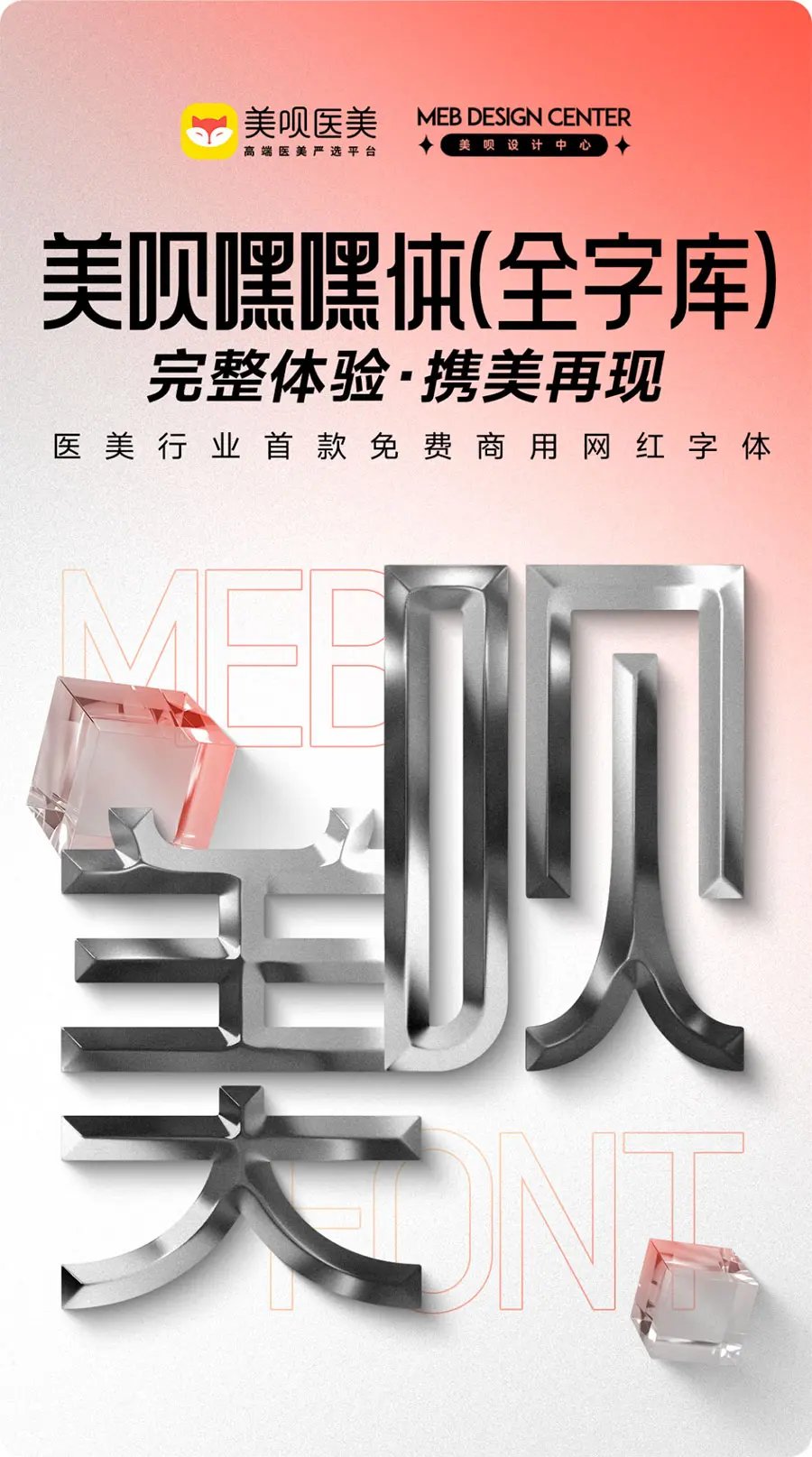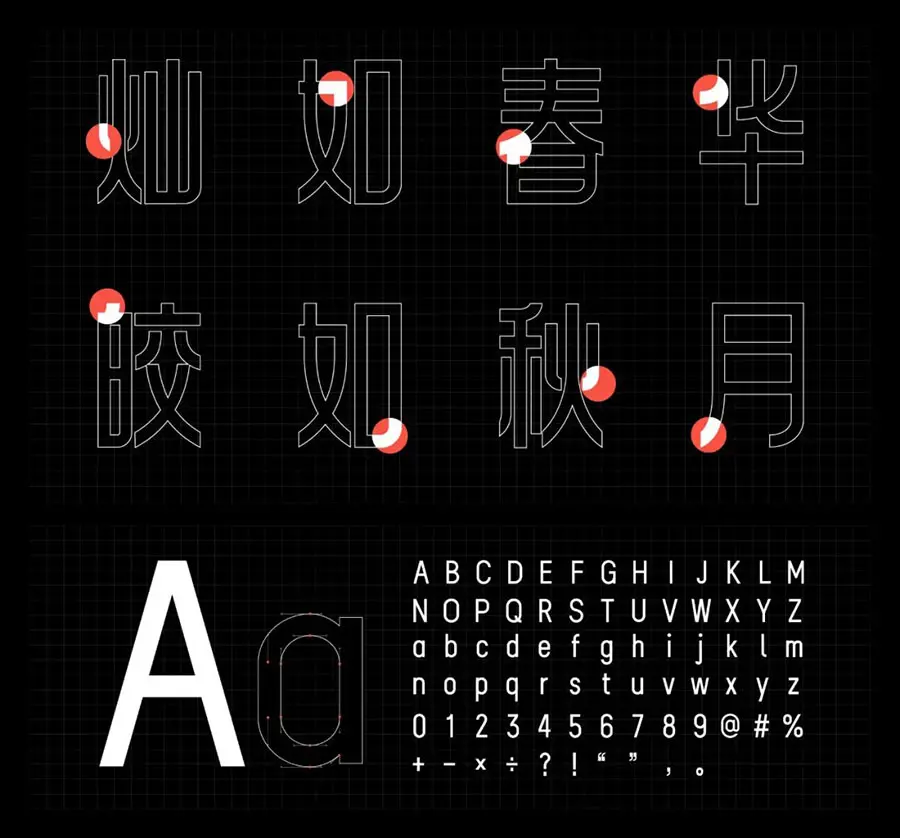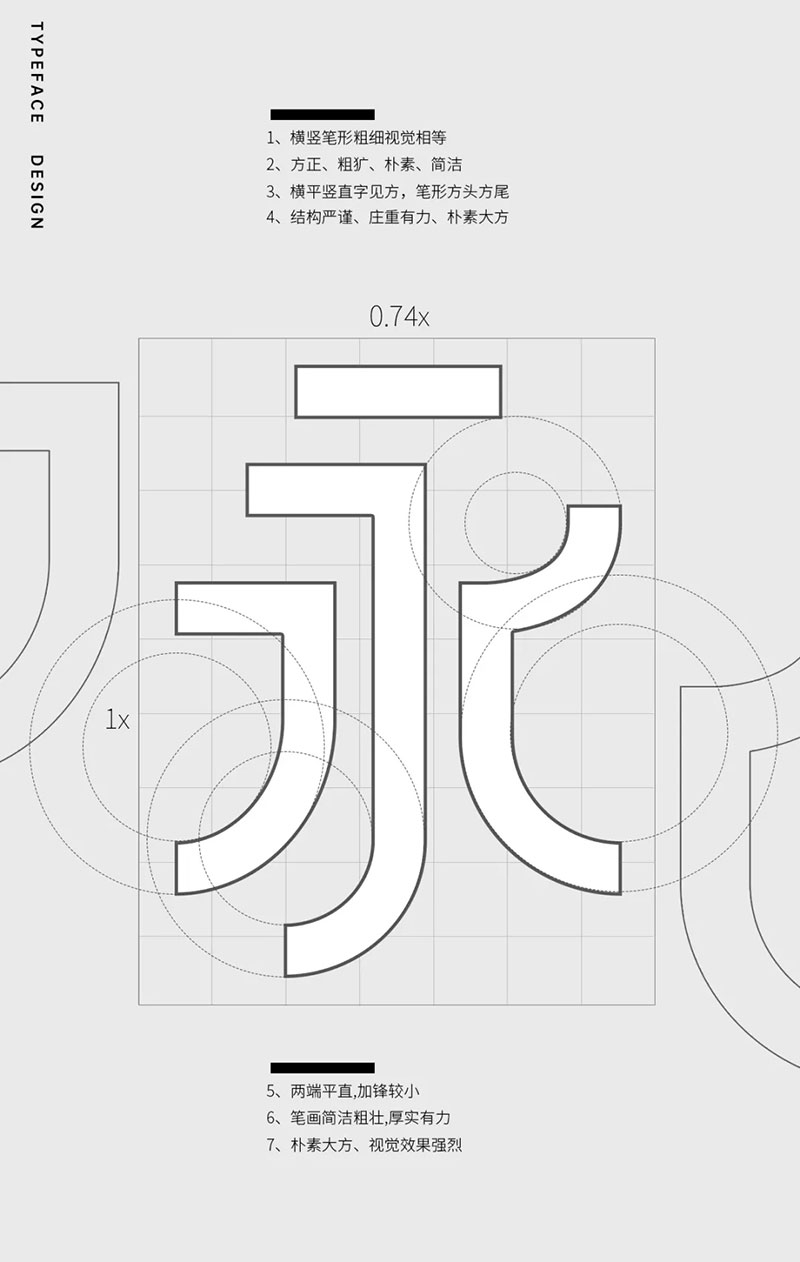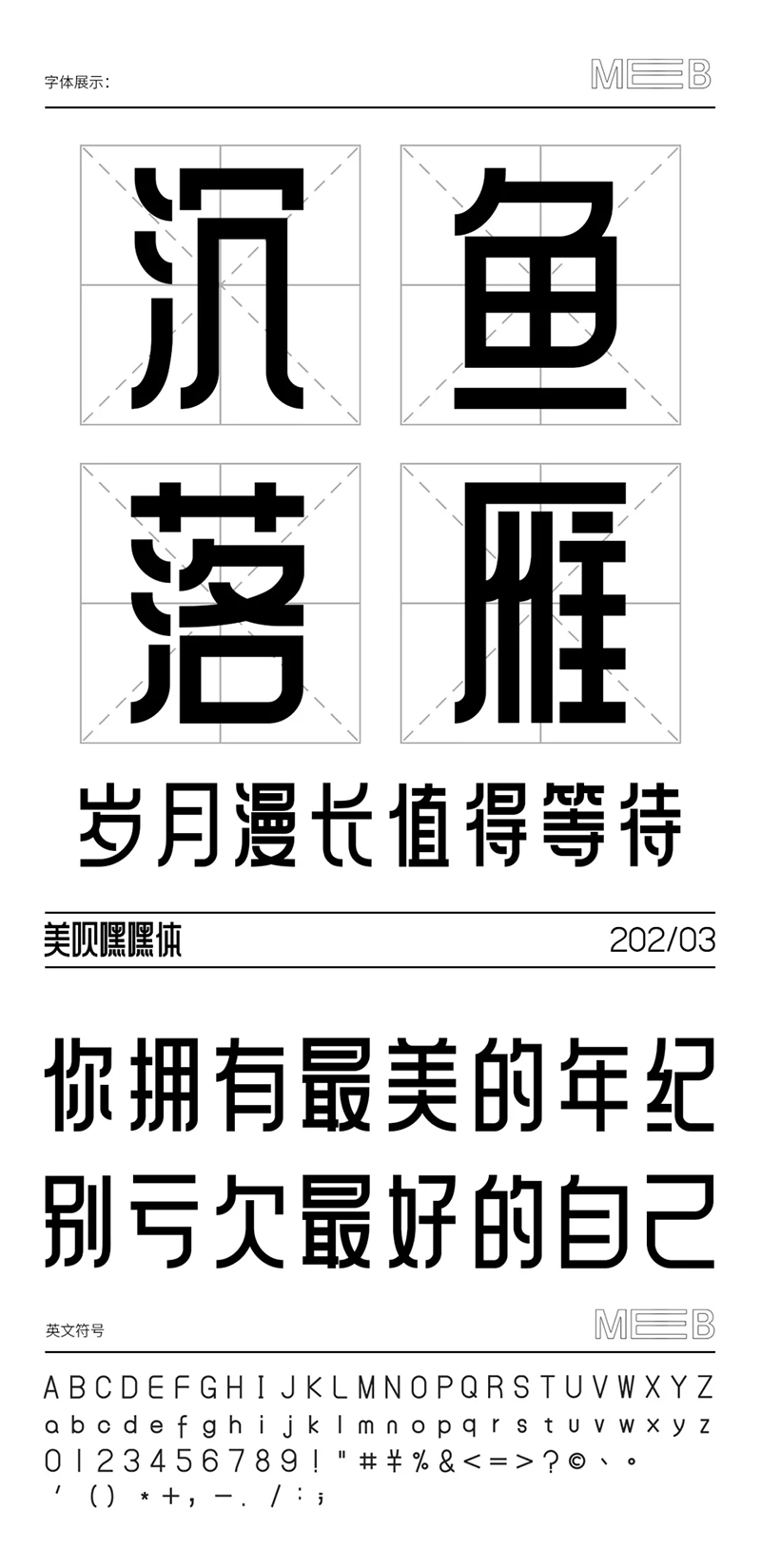
2021年11月1日,由美唄設計中心出品的首款免費商用字體【美唄嘿嘿體】試用版上線,包含2500+個漢字。
2022年末正式推出【美唄嘿嘿體】完整版啦!
美唄嘿嘿體,是由美唄設計中心主導設計的一款品牌字體,也是醫美行業首款字體。之所以取名美唄嘿嘿體,一是因為這款字體本身屬於黑體,二是融入了美唄人“樂觀、皮實”的精神,故取名“美唄嘿嘿體”。
秉承公司文化價值觀,設計團隊在工作之餘從構思到完成,整整花了兩年半的時間,精心打磨出了一套符合現代美業的商用字體。
這一年,我們也沒有停滯不前,在大家的反饋和期待聲中我們終於完成了美唄嘿嘿體(全字庫)的設計!符合GB2312簡體中文編碼字符標準的品牌字體,包含6767箇中文字符和150+西文及數字符號。
我們本著“大道至簡,大美天成”的設計理念,以極簡的筆畫形態使字體展現出一種自然美學。
在字形設計上,我們採用1:1.4的比例(白銀比例),相比西方比較流行的“黃金比例”,在東方更流行“白銀比例”,更能體現出低調內斂的東方之美。
相較於之前發佈的字庫,增加了4203箇中文字符,做了字體細節的微調,並且優化了西文及數字符號等,完成了我們給自己定的目標——打造一份屬於美唄的全字庫,也希望帶給大家更好的使用體驗感。
美唄一直在為東方女性提供美學服務,我們深知每一位女性都有其獨特的美,並且尊重每一種美。我們將11年深耕東方美學的經驗,刻入美唄嘿嘿體的設計中,賦予字體大氣的東方韻味和溫婉的東方美學,讓其不僅僅是一個個單調冰冷的字符,更是美唄對於美的理解和詮釋。現在免費供大家使用,也是希望能夠以己之美,成人之美。